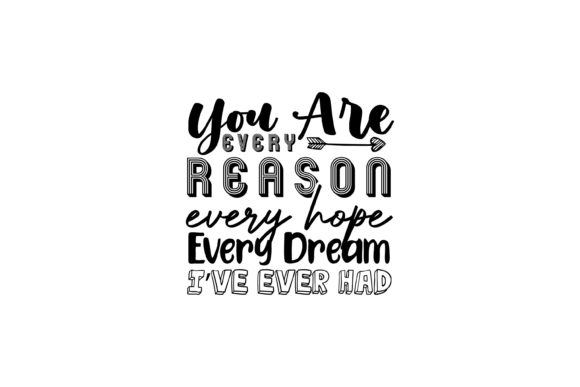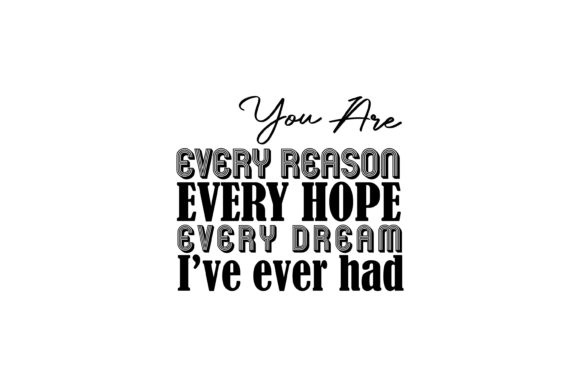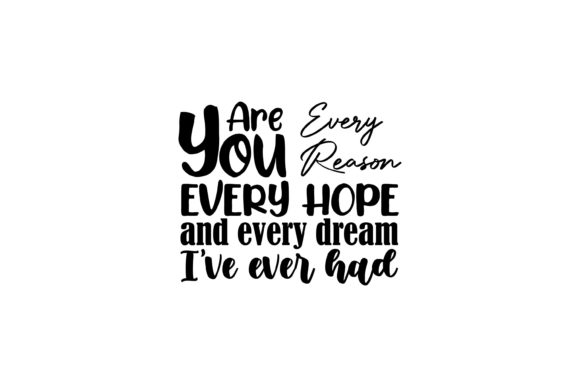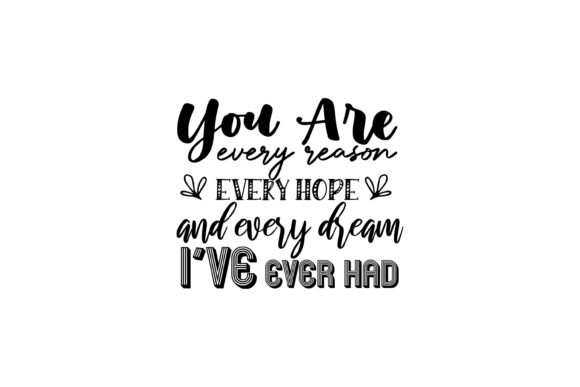
Every Dream-Love Quotes Font
หากคุณกำลังมองหาเนื้อหาคุณภาพสูงเช่น Every Dream-Love Quotes Font แพ็คเกจพรีเมียมนี้เป็นตัวเลือกที่ยอดเยี่ยมสำหรับโปรเจ็กต์สร้างสรรค์ของคุณ
ไม่ว่าคุณจะสร้างผลิตภัณฑ์ POD (Print on Demand) คำเชิญงานแต่งงาน หรือกราฟิกโซเชียลมีเดีย Every Dream-Love Quotes Font ก็เหมาะสมอย่างยิ่ง